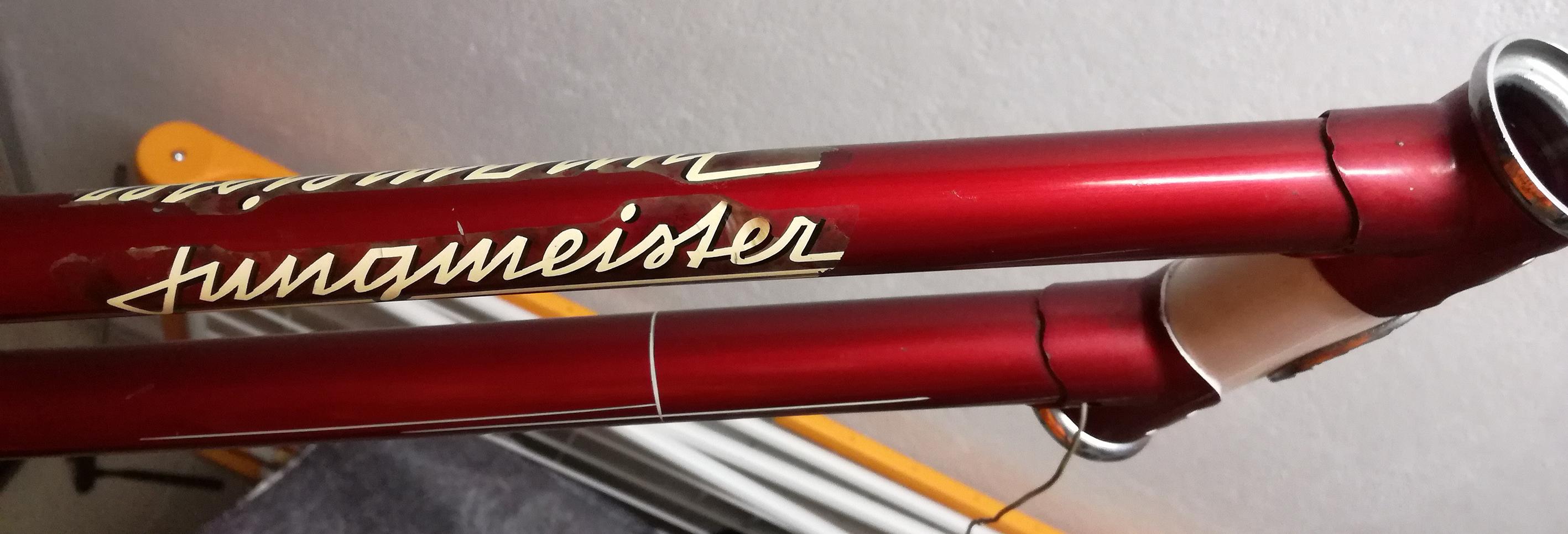
Schrift Puch „Jungmeister“ gesucht
suche die für den Schriftzug „Jungmeister“ verwendete Schriftart (siehe Bilddatei).
Der Aufkleber ist schon etwas beschädigt; beim „J“ fehlt offenbar der obere Arm.
Der Schriftzug stammt von der Fahrradserie PUCH Jungmeister aus den 1950er Jahren.